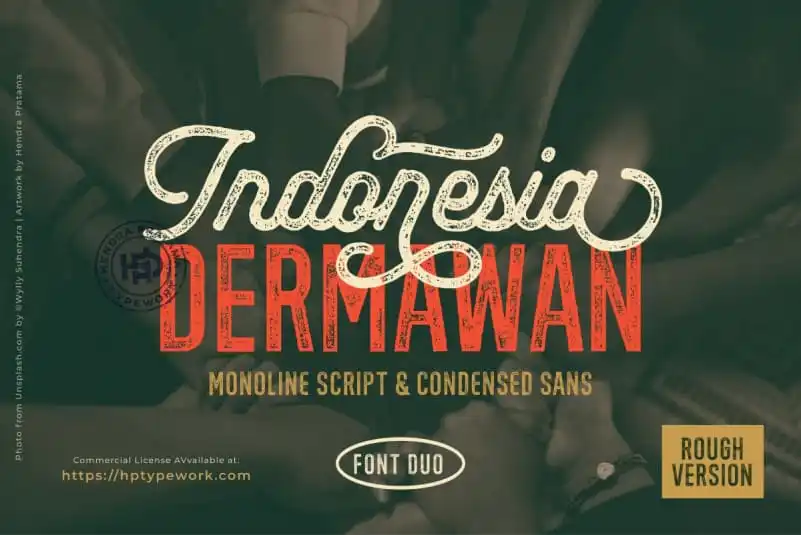
Indonesia Dermawan Display Font – Download Grátis
A Indonesia Dermawan Display Font surge como uma evolução inspiradora de letras vintage, criando um ambiente que remete a um aspecto antigo, sofisticado e artesanal. Essa fonte oferece uma sensação de elegância clássica e personalização única. Embora os caracteres maiúsculos apresentem alternativas elegantes, o destaque recai sobre as minúsculas, que contam com um rico leque de alternativas para que você possa escolher a que melhor se adapte ao seu estilo tipográfico. Ideal para adicionar personalidade e profundidade em projetos gráficos e websites, esta fonte atingirá o coração dos criativos. Seja ela usada para títulos impressionantes ou como parte do corpo da mensagem, a Indonesia Dermawan Display Font certamente destacará seu trabalho de forma única e sofisticada.